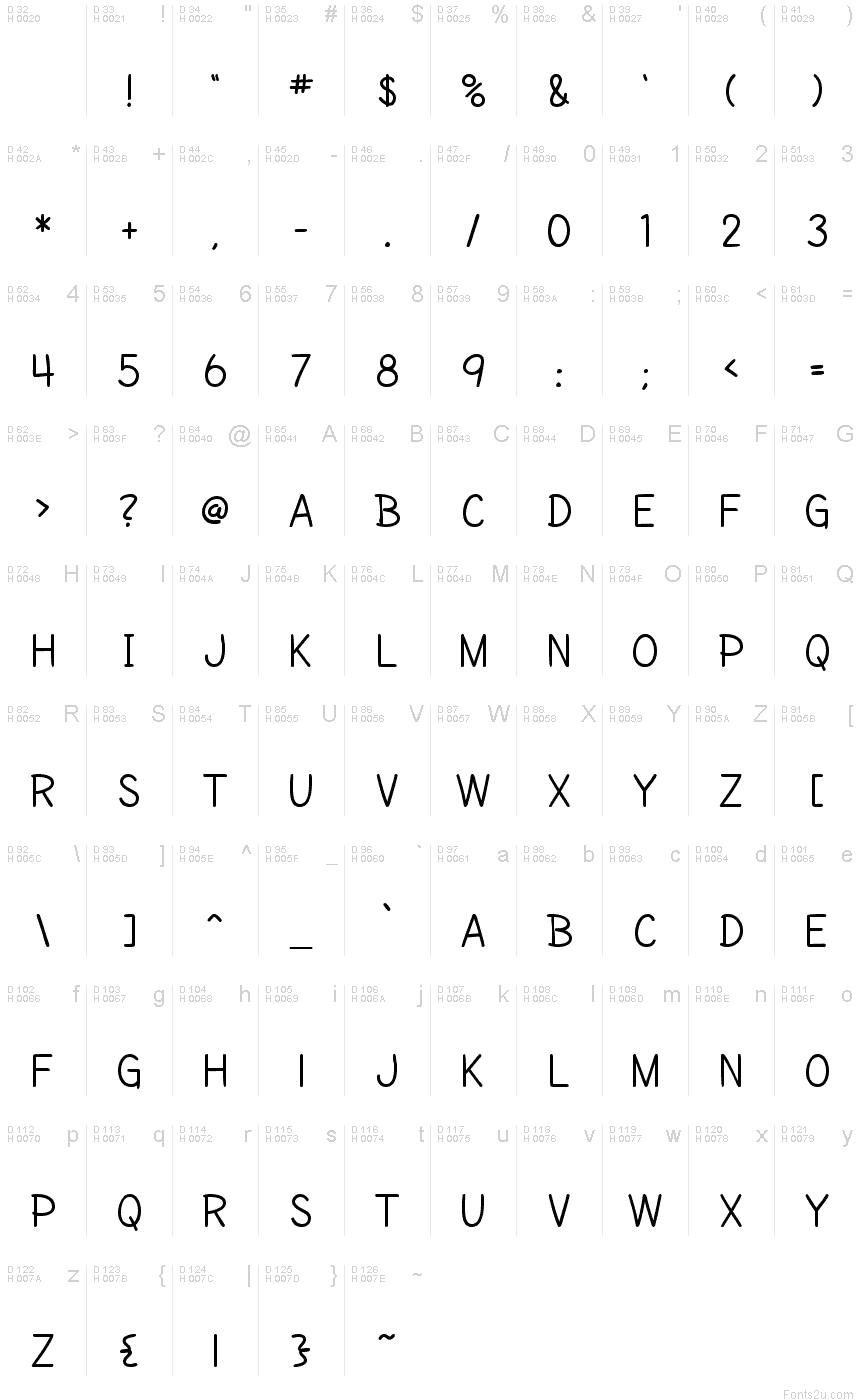
SF Cartoonist Hand SC di ShyFoundry è un font gratuito in stile fumetto con il tocco vivace e amichevole delle scritte a mano. Le lettere presentano curve alte e aperte e tratti leggermente irregolari che creano un ritmo naturale, mentre le forme semplificate donano un aspetto da cartone animato pulito, evitando l'effetto grezzo di uno schizzo.
Questo font gratuito è perfetto per titoli di poster, copertine di fumetti, grafiche per eventi dedicati ai bambini, packaging giocosi e cartelli dove desideri una scritta che sembri disegnata piuttosto che composta. È ideale anche per citazioni brevi o monogrammi, poiché le maiuscole restano audaci e leggere, senza inutili fronzoli.
Glifi del carattere SF Cartoonist Hand SC — Latino di base, pagina 1